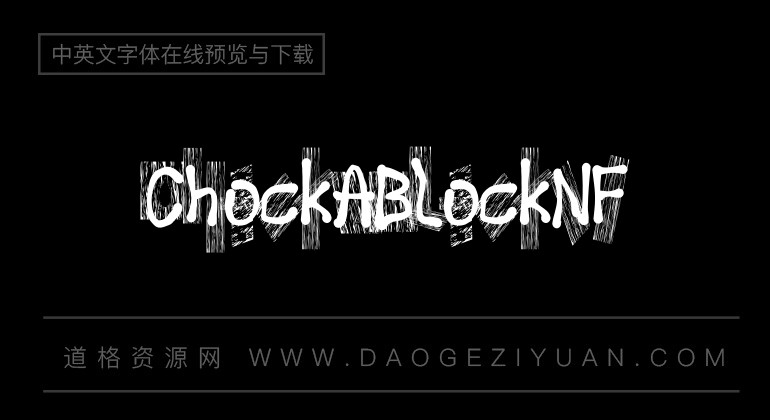
? ChockABlockNF 字体是一款由 Nick Curtis 创作的粗体脚本字体,它拥有独特的细节和设计,可以让您的文字更具吸引力。这款字体拥有多种字体风格,包括拉丁文、希腊文和日文,可以满足您的各种需求。它可以用于各种印刷品,从海报到书籍,也可以用于网站设计中。内容介绍
ChockABlockNF是一款非常不错的手写艺术字体,具有很好的视觉感,适合于文化类的宣传设计、商业类品牌的广告和产品包装设计以及个性化文字排版等较多场景。